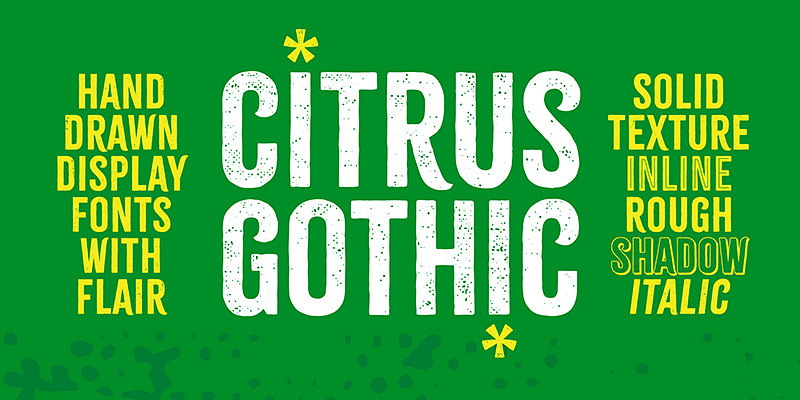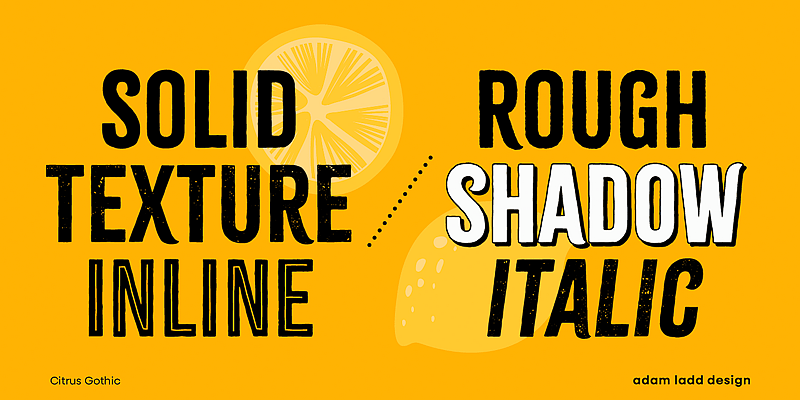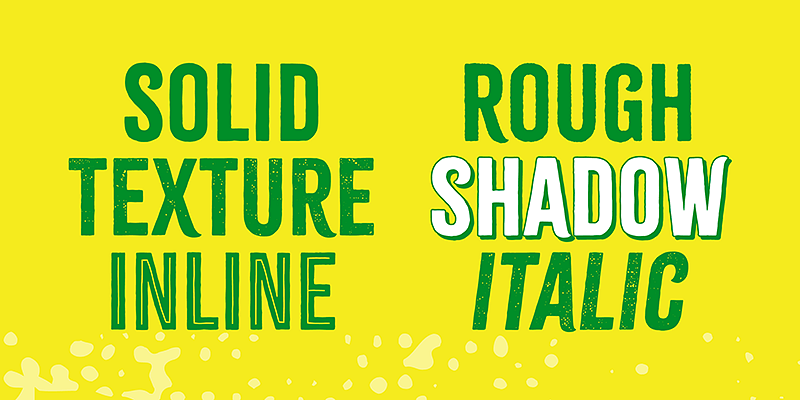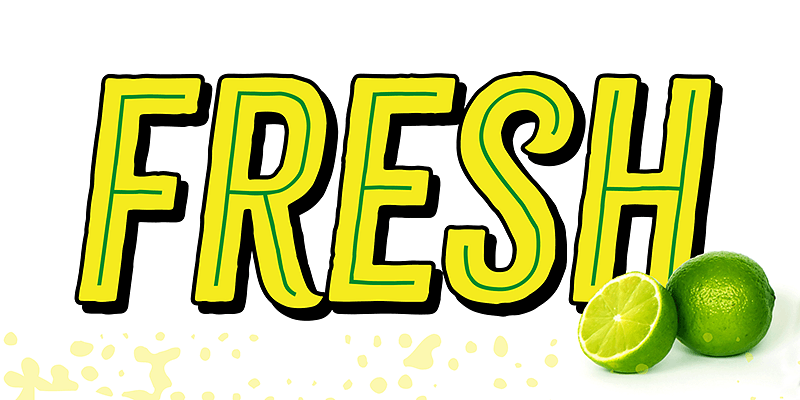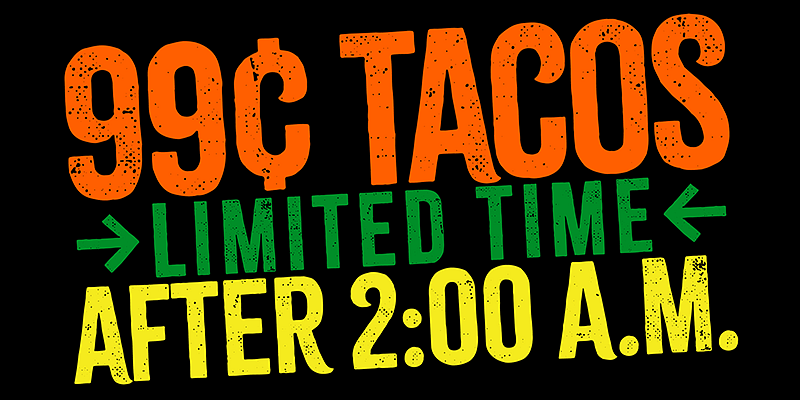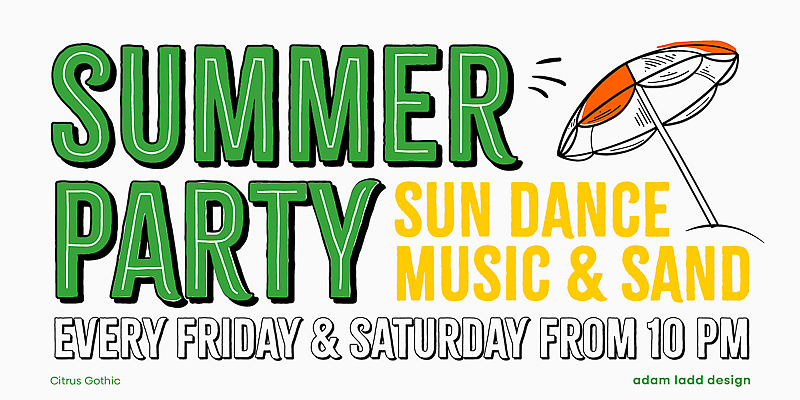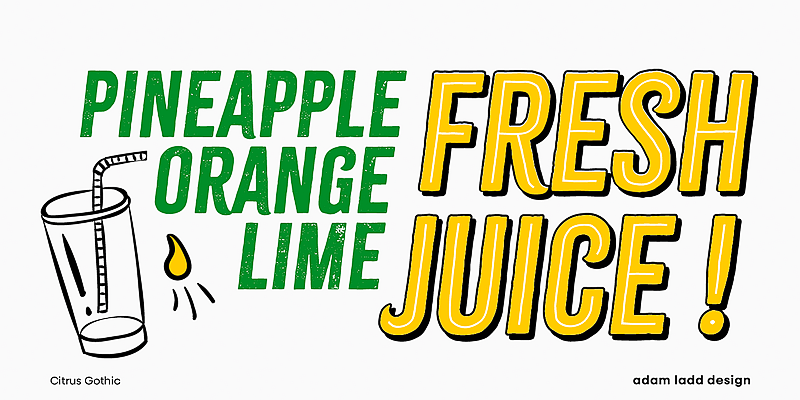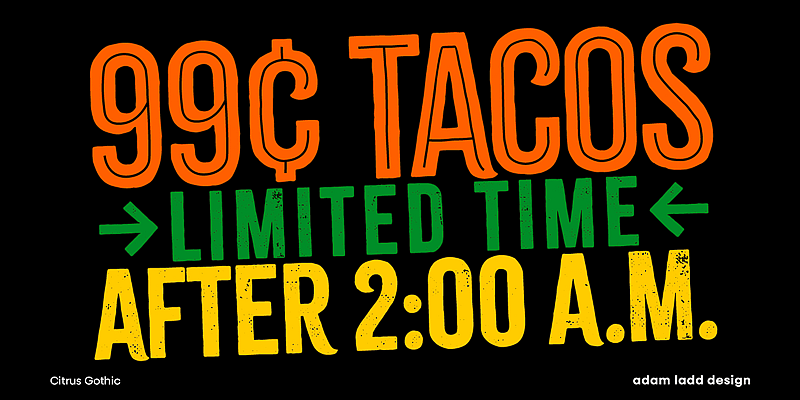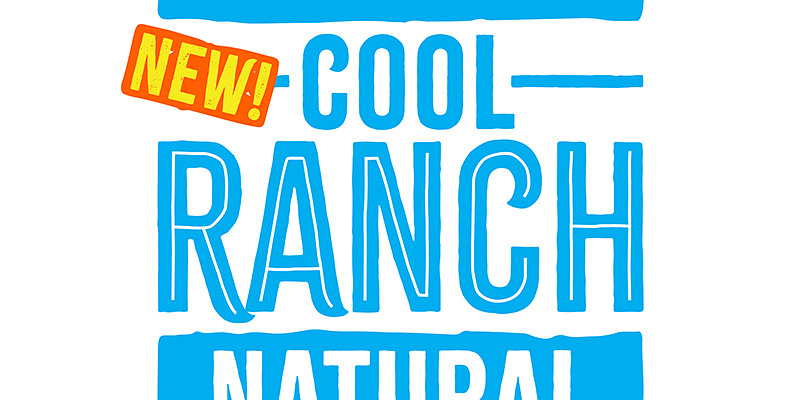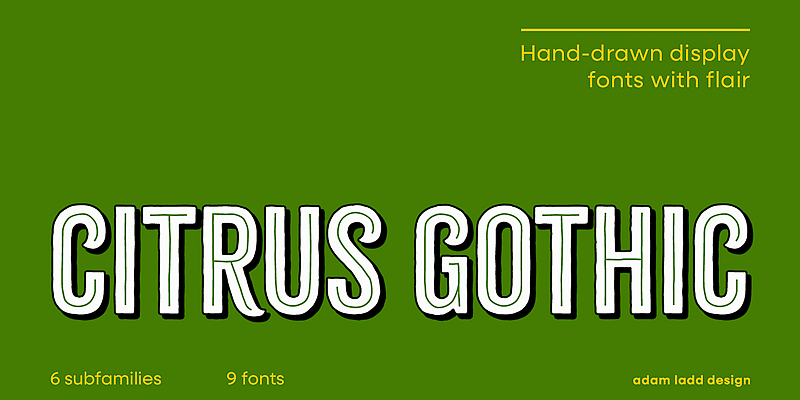
Al poner énfasis en tipos de letra diseñados para ser útiles y únicos, Adam Ladd elabora fuentes con un encanto diferente que plasma la estética moderna y vintage en estilos sans serif, serif y script. Su experiencia como director de arte en dos de las publicaciones de diseño más reputadas, las revistas HOW y PRINT, influye en su trabajo como diseñador tipográfico. Tanto clientes particulares como grandes empresas de multitud de industrias han comprado licencias de sus fuentes, como Disney, Whole Foods, Blizzard Entertainment y Penguin Random House.